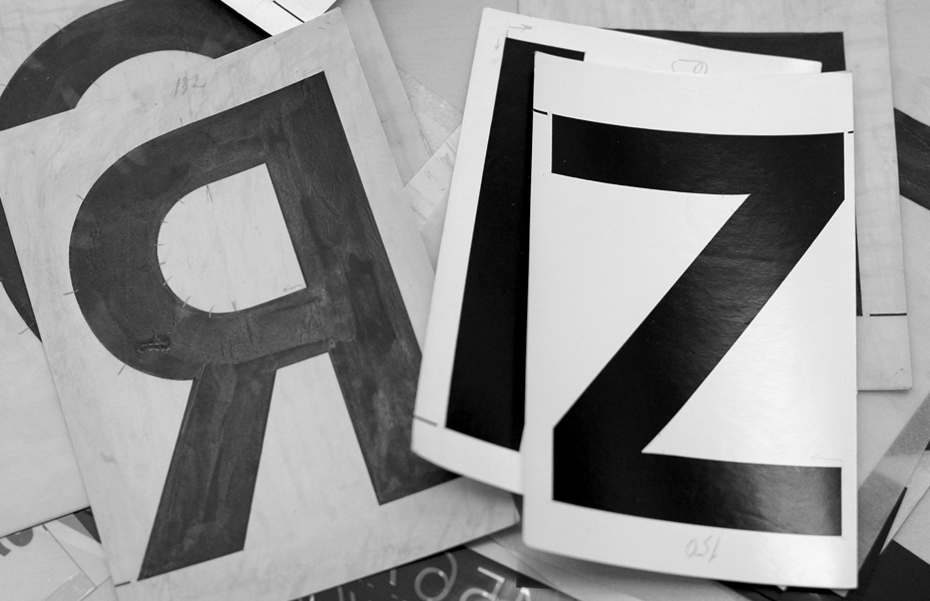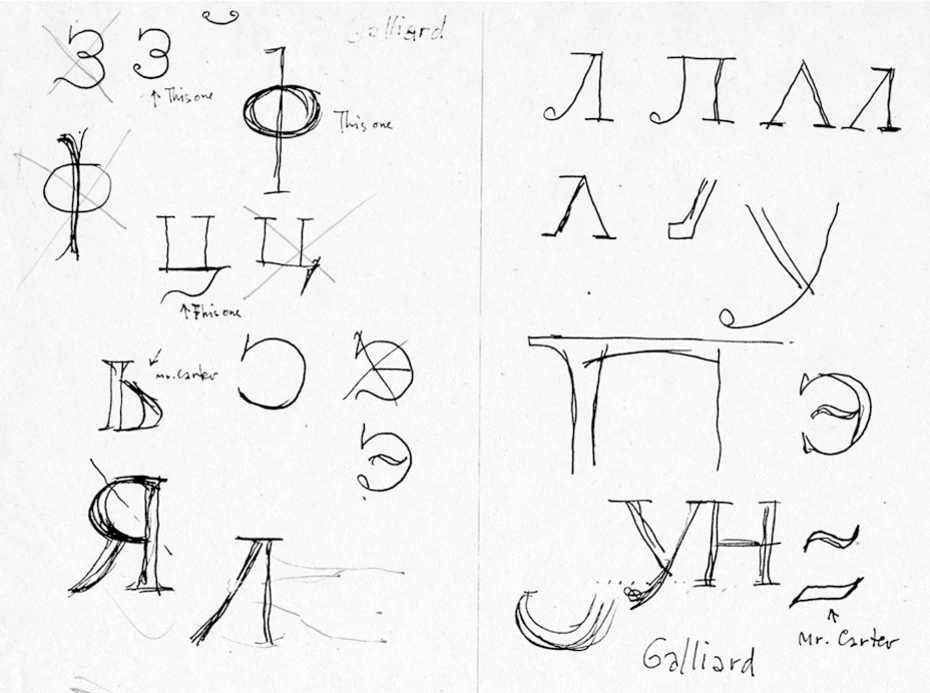
Интервью с Тагиром Сафаевым
ридцатилетний стаж в профессии дизайнера шрифта — для сегодняшней российской действительности явление довольно редкое. Тагир Сафаев прошёл путь от шрифтовых фотонаборных касс и сплайнов программы IKARUS, светящихся на ламповых экранах ЭВМ, до авторской школы шрифта и типографики. Бóльшая часть его шрифтов доступна в каталоге компании «ПараТайп», другие, зачастую эксклюзивные работы — неотъемлемая часть макетов международных издательских домов Axel Springer, Conde Nast и та­ких из­да­ний, как «Афи­ша», «Из­ве­стия», «Российская газета», и мно­гих дру­гих.
Тагир Ибрагимович, когда я увидел в первый раз ваш шрифт Куранта, то не смог найти практически никакой информации о нём, у меня был только плакат с интригующим текстом. Я заинтересовался его природой и пришёл, разумеется, к шрифту Vendôme, но у него наклонное начертание вместо курсива и много других особенностей. Расскажите об этом проекте.
Впервые я увидел Vendôme ещё в школе, тогда он поразил меня силой образа, каким-то притягательным мистицизмом, он настолько насыщен богатой традицией, что накрепко запомнился. Спустя много лет я как-то приобрёл кни­гу о фран­цуз­ском художнике Жор­же де Ла­ту­ре (Georges de La Tour, 1593–1652), и мастерство гениального француза запало в душу. В начале XVII века шрифты во Фран­ции делались всё ещё в парадигме Гарамона, но в это время ста­ло уже по­яв­лять­ся что-то но­вое. И вот, рас­смат­ри­вая Vendôme, я от­крыл для се­бя: это же и есть шрифт той са­мой эпохи. Тогда де Латур вдохновил меня, и я решил попробовать поработать с этим шрифтом, не представляя ещё, что из этого может получиться.
В книге Roger Excoffon et la fonderie Olive о шрифте Vendôme сказано, что эта динамичная и инновационная вариация в стиле Гарамона была работой скульптора, театрального художника Франсуа Гано (François Ganeau). Также указывается, что хотя Роже Экскоффон (Roger Excoffon) не был дизайнером этого шрифта, но он вдохновлял процесс его создания и руководил им, опираясь на своё тонкое стилевое чутьё.
Од­на­ко Vendôme оказался непростым, мно­го­слой­ным шрифтом, и эти слои, на мой взгляд, на­хо­дят­ся в не­ко­то­ром про­ти­во­ре­чии друг с дру­гом. Во-пер­вых, про­пис­ные — это мо­да 50-х го­дов на смелые оригинальные решения, выразительные острые детали, во-вто­рых — ка­жет­ся, что его занятные строч­ные буквы позаимствованы прямо из эпохи Гарамона. И в-третьих — это циф­ры, тоже из 50-х го­дов, но в них совсем иная пластическая интерпретация, нежели в прописных. Герард Ун­гер го­во­рит, что Vendôme — это экстраординарный Га­ра­мон. И ко­гда я ана­ли­зи­ро­вал этот шрифт, смог в этом убе­дить­ся. Вну­трен­няя борь­ба у ме­ня про­дол­жа­лась боль­ше го­да, по­ка я чи­тал де Ла­ту­ра и рас­смат­ри­вал его кар­ти­ны. Я на­чал за­ду­мы­вать­ся, как это можно ис­поль­зо­вать в качестве не­которой тра­ди­ции, что­бы на этом по­ле со­здать но­вое вы­ска­зы­ва­ние.
Шрифт Courante (Куранта), спроектированный Тагиром Сафаевым в 2010 году, — современная реконструкция образа французских барочных антикв начала XX века на основе шрифтов Vendôme (François Ganeau, Fonderie Olive, 1952) и Astrée (Robert Girard, Deberny et Peignot, 1921). Куранта включает в себя три гармонично согласованных системы письменности: латинскую, кириллическую и греческую. Стилистическое решение кириллической части выдержано в духе отечественных шрифтов первой половины XIX века, о чём могут свидетельствовать формы треугольных конструкций букв Л, л, Д, д, а также примечательная форма хвостиков Ц, ц, Щ, щ, подобия которых встречаются в эльзевировских шрифтах словолитни Маврикия Вольфа (Санкт-Петербург, 70–80-е годы XIX века).
Нужно сказать, что я следовал не какой-то конкретной цифровой версии, у меня их просто не было, моим ресурсом были изображения из различных изданий, причём они сильно отличались друг от друга — одно это возбуждало дух экспериментаторства. И в ито­ге я на­чал ра­бо­тать над со­от­вет­стви­ем про­пис­ных зна­ков строч­ным и об­щим един­ством шриф­та. Циф­ры, как полагается в антиквенных шрифтах, сде­лал ми­ну­скуль­ные, ка­пи­тель­ные и ма­юс­куль­ные. У Vendôme вме­сто кур­си­ва на­клон­ное на­чер­та­ние. Я сде­лал настоящий строчной кур­сив, от­ча­сти про­ци­ти­ро­вав кур­сив из фран­цуз­ско­го шриф­та Astrée (Robert Girard, Deberny & Peignot, 1923; позже он будет выпущен в Лондоне в 1926 году под именем Mazarin). И по­том та­кой слож­но­со­чинён­ный про­цесс стал про­дви­гать­ся даль­ше, что­бы сло­жить­ся в не­что еди­ное. В об­щем, счи­таю, что работа по­лу­чи­лась и её нуж­но бы про­дол­жить и за­вер­шить.
С 1995 года в мире было сделано не менее пяти цифровых версий Vendôme. Например, Кристиан Шварц (Christian Schwartz), американский дизайнер, разрабатывал свою версию этого шрифта, но работа осталась незаконченной. Думаю, что это естественный подход к историческим шрифтам — наполнять создаваемый шрифт не­ко­ей су­ще­ству­ю­щей тра­ди­ци­ей и по ме­ре спо­соб­но­стей вно­сить свою ин­то­на­цию, свои пла­сти­че­ские со­об­ра­же­ния, то­гда мо­жет появиться шанс со­здать не­что но­вое и ин­те­рес­ное. Примеров такого подхода множество! В том, что мы транс­фор­ми­ру­ем, раз­ви­ва­ем что-то уже су­ще­ству­ю­щее, нет ни­ка­ко­го «правового про­из­во­ла», на­про­тив, ис­то­ри­че­ский об­ра­зец помогает в начале работы точнее понять задачу, ко многому обязывает в процессе работы, что приводит в конце концов к внятному результату, у ко­то­ро­го бу­дут кон­крет­ные кри­те­рии оцен­ки.
Вы закончили Полиграфический институт и именно там обнаружили интерес к шрифту. Расскажите о вашей учёбе и о том, как вы появились в шрифтовом деле.
Да, со шриф­том я столк­нул­ся, по­сту­пив в По­ли­граф в 1984 го­ду. Мне бы­ло уже за 30, и я ра­бо­тал по ли­нии Со­ю­за ху­дож­ни­ков в гра­фи­ке, цвет­ном эстам­пе. С се­ре­ди­ны 70-х мо­ей основ­ной ра­бо­той в худфонде, ку­да ме­ня на­пра­ви­ли по окон­ча­нии ху­до­же­ствен­но­го учи­ли­ща (1971), ста­ла мо­ну­мен­таль­ная рос­пись в об­ще­ствен­ных зда­ни­ях Астра­ха­ни и об­ла­сти. При­ме­ром мо­гут слу­жить рос­пи­си в ак­то­вом за­ле астра­хан­ской су­до­вер­фи им. С. М. Ки­ро­ва, в фойе го­род­ской шах­мат­ной шко­лы и дру­гие.
В на­ча­ле 80-х я по­пал в дом творчества «Че­люс­кин­ская», где ру­ко­во­ди­те­лем по­то­ка был Алек­сандр Ли­ва­нов. Это уди­ви­тель­ная лич­ность, за­ме­ча­тель­ный пе­да­гог. Я про­сто не от­хо­дил от него, без конца со­ве­то­вал­ся с ним. Кро­ме то­го, сам по­ток со­сто­ял из большого количества про­фес­си­о­на­лов. Ли­ва­нов мне на мно­гое от­крыл гла­за, до­мой я при­е­хал про­сто дру­гим че­ло­ве­ком. В ито­ге я по­нял, что мне не хва­та­ет об­ра­зо­ва­ния, и ре­шил в свои 33 го­да по­сту­пать в ин­сти­тут.
И по­сту­пил, но че­рез не­ко­то­рое вре­мя на­чал со­мне­вать­ся: за­чем я во­об­ще это сде­лал? Ока­за­лось, что Ли­ва­нов там ещё не пре­по­даёт (он стал пре­по­да­вать че­рез три го­да), об­ще­ствен­ные пред­ме­ты — од­на ис­то­рия пар­тии че­го сто­ила — по­гло­ща­ют бóльшую часть времени. Так в неопределённости про­шла не­де­ля, по­ка в суб­бо­ту не по­явил­ся Мак­сим Жу­ков. Буквально после первых занятий у ме­ня пробудился огромный ин­те­рес к шриф­ту и на­чал­ся все­сто­рон­ний про­цесс осо­знан­но­го на­коп­ле­ния зна­ний. То­гда я ото­дви­нул гра­фи­ку и на­чал за­ни­мать­ся ис­клю­чи­тель­но шриф­том.
Именно по-настоящему профессиональное преподавание шрифта с са­мо­го на­ча­ла побудило меня по­грузиться в те­му, рас­смат­ри­вать шрифт в кон­тек­сте ис­то­рии ис­кусств, ли­те­ра­ту­ры, языка, общества и ещё много чего.
Во вре­мя обу­че­ния я по­зна­ко­мил­ся также с Алек­сан­дром Ко­но­плё­вым, ди­зай­не­ром кни­ги. Че­рез Ко­но­плёва и Жу­ко­ва я мно­гое по­стиг в ти­по­гра­фи­ке, в книж­ном ди­зай­не. Ещё был Ми­ша, Михаил Александрович Аникст, ко­лос­саль­ная лич­ность, — я на­про­сил­ся прой­ти прак­ти­ку в его ма­стер­ской, которая была в то время как бы эпицентром, притягивающим молодых людей, вовлечённых в графический дизайн. Чем только не занимался Миша — от кни­г, альбомов до пла­ка­тов, ло­го­ти­пов и прочей айдентики. То­гда все об­хо­ди­лись не­боль­шим ас­сор­ти­мен­том шриф­то­вых касс, а у Ми­ши бы­ло ги­гант­ское ко­ли­че­ство фо­то­на­бор­ных касс — чувство шрифта было на высоте. Не бы­ло ком­пью­те­ров и ска­не­ров — мы вы­чи­ща­ли фо­то­гра­фии, сни­ма­ли, уве­ли­чи­ва­ли, умень­ша­ли, вы­кле­и­ва­ли. Лю­ди всю жизнь этим за­ни­ма­лись, а у Ми­ши представился случай освоить это за год с небольшим. Я по­нял зна­че­ние руч­но­го тру­да для шриф­то­во­го де­ла, все эти умень­ше­ния, мас­шта­би­ро­ва­ния. Это очень по­лез­но — ощу­щать зре­ни­ем, ру­ка­ми. Он первый указал, что дизайнер может и должен вести параллельно с дюжину разнообразных работ, эта динамика позволяет глубже понимать суть профессии.
Темой вашего дипломного проекта стала кириллизация шрифта Frutiger, который позже был выпущен под именем FreeSet. Почему вы выбрали именно его?
Вообще-то, сначала я выбрал дипломным проектом кириллизацию шрифта ITC Slimbach. Но Миша предложил другую идею: «Вот немецкий журнал Form, он набирается шрифтом Frutiger (в 80-х годах в Европе этот шрифт как раз вышел в полной латинской комплектации), хорошо бы иметь его у нас в кириллице». Тогда меня этот журнал поразил качеством дизайна, чистотой исполнения типографических и шрифтовых решений.
В итоге темой моего диплома была кириллизация «Фрутигера», эта работа поглотила меня целиком. Руководителем диплома был Владимир Ефимов — и это тоже было невероятным везением. Ефимов в институте не работал, я его не знал лично. Тогда я попросил Коноплёва познакомить меня с Ефимовым, он позвонил и говорит: «Володя, вот тут студент, хочет, чтобы ты вёл его диплом. Приходи, или он к тебе придёт». Вот я к нему и пришёл и шаг за шагом начал изучать форму кирилловских букв — это была целая наука.
В ито­ге все пять лет я занимался толь­ко шриф­том. На ка­фед­ре по­ня­ли, что жи­во­пис­цем или гра­фи­ком не ста­ну, пя­тёр­ки, прав­да, ста­ви­ли — ра­бо­ты-то у ме­ня хо­ро­шие бы­ли, Cо­юз ху­дож­ни­ков всё-та­ки за пле­ча­ми, и, видимо, пригодился опыт работы в ли­то­гра­фи­и и гра­вю­ре. Ди­плом у ме­ня был на шесть ли­стов фор­ма­та А1: сплошные бук­вы, два пря­мых на­чер­та­ния. Получил пятёрку.
Потом обучение закончилось, это был 1989 год, перестройка шла полным ходом — выпускников вузов уже не так настойчиво отправляли «по направлению» в города и веси. Поэтому я, немного отдышавшись в Астрахани, вернулся в Москву, снял комнату, перебивался маленькими работами по издательствам.
А в 1990 году начались перемены: появилась шрифтовая фирма Azzet, правда, они занимались пиксельными шрифтами. Другая фирма родилась в недрах ОНШ (отдел наборных шрифтов в НИИ «Полиграфмаш»), который присоединился к фирме ParaGraph Int., тогда это называлось советско-американским предприятием, они занимались векторными шрифтами.
Кто в те годы работал в «ПараГрафе»?
События развивались следующим образом. Сначала побывал на встрече в Azzet. Там уже работали Дмитрий Абрикосов, мой сокурсник, Женя Добровинский, Виктор Кучмин — всё знакомые лица. Там в первый раз увидел компьютер. Пока размышлял, что буду делать в Azzet, встретился с Володей Ефимовым, он объявил, что создаётся солидная фирма ParaGraph и в ней будет шрифтовой отдел, и говорит: «Давай-ка ты лучше к нам, в „ПараГраф“». Я прикинул — вроде там тоже интересно, тем более мы с Ефимовым во время работы над дипломом хорошо сработались. И самое главное, они занимались вектором, а не пикселями, с профессиональной точки зрения мне это казалось солиднее. И я пошёл в «ПараГраф».
Располагался он тогда на Трубной, 7, наш отдел размещался в крохотной комнатушке — духотища, жарища, но именно там я впервые сел за компьютер. Мы были шрифтовым отделом «ПараГрафа». Там работали Володя Ефимов, Саша Тарбеев, Любовь Алексеевна Кузнецова, Эльвира Сергеевна Слыш, Исай Соломонович Слуцкер — он уже в возрасте был. Просто звёздный состав. Помните такой шрифт — ITC Franklin Gothic, так вот, когда я увидел, среди прочих букв, рисунок строчной буквы «б», который сделал Исай Соломонович, меня восхитил масштаб его опыта и умений. Это была тонкая и точная работа — он нашёл то самое движение, которое подходит и по пропорциям, и по масштабу. Эта точность и является смыслом нашей работы. Если её нет или нет стремления к этой точности, лучше чем-то другим заниматься.
Шрифт ITC Franklin Gothic Cyrillic. Цифровая версия гарнитуры разработана в фирме International Typeface Corporation в 1980 году (дизайнер Виктор Карузо). Franklin Gothic был спроектирован Моррисом Бентоном и первоначально выпущен фирмой American Type Founders в 1904 году. Версия ITC широко развита по насыщенности и, при слегка зауженных пропорциях и крупном очке строчных знаков, может применяться для набора текста, заголовков и акциденции. Кириллическая версия разработана в фирме «ПараТайп» («ПараГраф») в 1995 году (дизайнеры Исай Слуцкер, Татьяна Лыскова). 12 узких начертаний были добавлены в 2000 году Исаем Слуцкером и Дмитрием Кирсановым.
И с начала 90-х вы c коллегами работали над кириллизацией западных шрифтов, в результате чего в арсенале российских дизайнеров появились приличные шрифты с кириллицей: Баскервиль, Гарамон, Чартер, Франклин Готик, Футура и целый ряд других.
Да, то­гда бы­ла об­щая про­бле­ма: в Рос­сию при­бы­ва­ло всё боль­шее и боль­шее количество ком­пью­те­ров со встро­ен­ны­ми в них си­стем­ны­ми шриф­та­ми, к сожалению, ки­рил­ли­ческих расширений эти шриф­ты не имели, нашим дизайнерам просто не­чем бы­ло ра­бо­тать.
Но опять по­вез­ло: Мак­сим Жу­ков был зна­ком с людь­ми из International Typeface Corporation, и он по­мог «Па­ра­Гра­фу» до­го­во­рить­ся с ITC, что­бы мы мог­ли ки­рил­ли­зо­вать шриф­ты из биб­лио­те­ки. Под­лин­ные ри­сун­ки знаков, ко­то­рые ITC при­сы­лал, по тем вре­ме­нам были невообразимого ка­че­ства.
Затем началась работа, консультации Максима, которые для меня были как бы продолжением образования, начатого ещё в институте. Потрясающее было время.
То­гда был на­сто­я­щий бум! Мак­сим пра­виль­но го­во­рит, что бы­ли «ли­хие 90-е», но для шрифтового цеха это было нечто другое — лю­ди тру­ди­лись и со­зда­ва­ли ба­зу, о которой он рассказал в статье в сборнике Language Culture Type. По мо­е­му мне­нию, в ис­то­рии оте­че­ствен­но­го шриф­то­во­го де­ла со времён ре­фор­м Пет­ра I бы­ло несколько значимых эта­пов, один из которых — ко­нец именно на­ше­го XX ве­ка, ко­гда оте­че­ствен­ный шриф­то­вой ре­пер­ту­ар рас­ши­рил­ся на осно­ве ка­че­ствен­но кириллизованных за­пад­ных шрифтов. Здесь сублимировался огромный предыдущий опыт, традиции латиницы и кириллицы и понимание требования времени.
Вы начинали работать в «Икарусе»?
Мои познания в компьютерных программах минимальны. С годами, конечно, растёт осведомлённость, но акцент у меня всегда в зоне формы буквы, на визуальной точности контура, а не в программном языке описания этого контура, хотя, конечно, в мире требования к программной стороне дела возрастают и дизайнеру рекомендуют «учить матчасть».
С появлением персонального компьютера у программиста ОНШ Андрея Скалдина, естественно, появилась идея переложения системы IKARUS, которая работала на больших производственных компьютерах, на РС. Эта новая программа называлась Fontain, она предназначалась для работы шрифтовых дизайнеров в «ПараГрафе». Во всём мире дизайнеры шрифта работали в программе Fontographer. Разница этих программ была существенной: Fontain имел дело со сплайнами, а Fontographer — с кривыми Безье.
Как раз свой дипломный шрифт FreeSet я делал на опытных версиях программы Fontain, но из-за технических трудностей пришлось работать на оригинальном «Икарусе» в ОНШ. Внешне это огромный тёмно-зелёный, почти чёрный экран монитора, на котором тоненькая ярко-зелёная линия — это контур буквы в сплайнах. При нажатии пары клавиш программа конвертирует контур в кривые Безье, и появляется тоненькая ярко-красная линия. Получил контур, распечатал на плоттере, закрыл тушью — смотришь. Поучительная программа была — приучала чувствовать едва заметные изменения контура в сплайнах, стараться, чтобы они в Безье правильно отображались при конвертации.
Каким был следующий шрифт после Фрисета?
По­сле Фри­се­та я, ко­неч­но, хо­тел за­мах­нуть­ся на ITC Га­ра­мон, но это­го не слу­чи­лось: Га­ра­мон до­стал­ся Са­ше Тар­бе­е­ву. Всё к луч­ше­му. По­ру­чи­ли ITC New Baskerville. Мне по­вез­ло вдвой­не. Во-пер­вых, ITC New Baskerville — вы­со­кая клас­си­ка в чи­стом ви­де. Гар­ни­ту­ра бы­ла ли­цен­зи­ро­ва­на фир­мой ITC в 1982 году у фир­мы Mergenthaler Linotype. Это раз­ра­бот­ка Джо­на Ка­ран­та 1978 го­да. Вто­рое: по­лу­чив кар­тин­ки со шриф­та­ми, ста­ло из­вест­но, что Мак­сим Жуков бу­дет кон­суль­ти­ро­вать на­шу ра­бо­ту. Его ком­мен­та­рии к шриф­там мы по­лу­ча­ли по­чтой, чи­та­ли их и ис­прав­ля­ли сде­лан­ное — он пи­сал про каж­дую бук­ву, что с ней нуж­но сде­лать. Во­об­ще, очень важ­но бы­ло уча­стие Мак­си­ма в про­ек­тах шриф­тов ITC, это труд­но пе­ре­оце­нить.
В 1982 году аме­риканс­кая фирма ITC ли­цен­зи­рова­ла у фирмы Mergenthaler Linotype новый ва­ри­ант шриф­та Baskerville и назвала его ITC New Baskerville в 8 на­чер­та­ни­ях. Он был соз­дан груп­пой ди­зай­не­ров под ру­ководс­твом Джона Ка­ран­та. Ки­рил­ли­чес­кую вер­сию этого шриф­та для компании «ПараТайп» раз­ра­ботал в 1993 году Тагир Са­фа­ев.
На­при­мер, я сра­зу улав­ли­вал, о чём Мак­сим пи­шет, от­ку­да у не­го воз­ни­ка­ет та или иная идея. Мак­сим ведь за­кон­чил учё­бу в середине 60-х и с тех пор систематически работал над шрифтами, шёл к однажды выбранной цели. В со­вет­ское вре­мя шриф­то­вой ди­зай­нер мог толь­ко на об­лож­ку «Ко­лоб­ка» или «Гро­зы» Остров­ско­го на­ри­со­вать что-то — и всё! А Мак­сим, с его глубокими познаниями, де­ся­ти­ле­ти­я­ми вы­на­ши­вал идеи для ки­ри­ллов­ских шриф­тов. И аль­янс с ITC — это ре­а­ли­за­ция замыслов, зревших в те са­мые де­ся­ти­ле­тия.
Вы проектировали кириллицу для нескольких проектов Мэтью Картера. Такого рода сотрудничество, конечно, дорогого стоит. Как выстраивалась работа с мистером Картером?
Это вер­но. На шриф­тах Мэтью Кар­те­ра, мож­но ска­зать, я вы­рос! Их было несколько. В 1995 го­ду в «Па­ра­Гра­фе» решили ки­рил­ли­зовать два шриф­та, и это нуж­но бы­ло с че­стью вы­пол­нить: ITC Charter и ITC Galliard. По­сколь­ку оба шриф­та сде­лал Кар­тер, не бы­ло ре­чи, что луч­ше или ху­же. Мы с Во­ло­дей вы­ки­ну­ли на паль­цах, кому что достанется, вышло: ему — Чар­тер, мне — Га­льярд. Если честно, хотелось именно ITC Galliard, потому что это легенда, его характеризуют как мощный, буйный, яркий, даже чувственный. Поразительная история у этого шрифта!
Мэтью Картер сделал шрифт Galliard в 1978 году для фотонаборных машин компании Mergenthaler Linotype Company. В журнале U&lc; 1981 года под рубрикой What’s new from ITC перед крупно напечатанными алфавитами Galliard’a сказано: «Эта прекрасная современная реконструкция шрифтов [французского художника шрифта, гравёра и печатника] Робера Гранжона (Robert Granjon, 1513–1590) XVI столетия была создана дизайнером Мэтью Картером. Картер использовал компьютер, чтобы спроектировать систему начертаний, соответствующую требованиям XX века. <...> Дизайнер Картер провёл очень деликатную работу, воплотив дух шрифтов Гранжона в современной разработке, отличающейся подтянутой, энергичной формой знаков и высоким ростом строчных. Прямые и курсивные начертания при всей своей выразительности прекрасно читаются в наборе объёмных текстов».
Картер писал письма, в которых он очень подробно комментировал, что и как нужно сделать, всё было очень цивильно оформлено: на бланке, без суеты. Он присылал выведенные с пантографа изображения кирилловских букв, которых не хватало, я их сканировал и работал уже с ними.
Как вы­стра­и­ва­лась ра­бо­та Кар­те­ром? В основном я работал с Максимом, а он уже общался с Картером, когда что-то было непонятно. Максим, естественно, с ним советовался. У меня сохранилась картинка, на которой Максим рисовал формы, показывал мистеру Картеру, а тот уже дорисовывал. Например, написано: я такая может быть, а он — No. А вот мистер Картер нарисовал, как Ц курсивную нужно делать или как г курсивную — там сложнейшая форма.
К со­жа­ле­нию, ко­гда я за­кон­чил два на­чер­та­ния, в 1995–1996 го­дах, у ITC воз­ник­ли про­бле­мы, а в 2000 го­ду они сменили владельца. Было объявлено о «смутном времени». Но­вое ко­ман­до­ва­ние отложило ITC Galliard в план следующего года. Проект, над ко­то­рым я ра­бо­тал около го­да, остал­ся не­за­вер­шён­ным. Я бы сей­час с боль­шим удо­воль­стви­ем про­дол­жил ра­бо­ту над Га­льяр­дом. По­тря­са­ю­щей кра­со­ты шрифт.
Вопрос о шрифте Cheltenham. Я видел две версии шрифта для разных макетов — для журнала Forbes и для русскоязычного издания The New York Times и помню, что меня удивило, насколько разным был образ и даже возраст кириллицы в этих шрифтах.
Это для ме­ня це­лая эпо­ха. Ко­гда я ра­бо­тал для «Форб­са», то сде­лал пер­вое на­чер­та­ние ITC Cheltenham. Во­об­ще, Cheltenham — это пре­крас­ная мо­дель. Сам шрифт спро­ек­ти­ро­вал в 1896 го­ду Бер­трам Гуд­хью (Bertram Grosvenor Goodhue) и Ин­галс Ким­бол (Ingalls Kimball) для Cheltenham Press, а позд­нее его пе­ре­ра­бо­тал Мор­рис Бен­тон (Morris Fuller Benton) для American Type Founders Company. И эти вер­сии силь­но от­ли­ча­ют­ся по сво­е­му ду­ху от то­го, что сде­лал по­том ITC. На са­мом де­ле у шриф­та бо­лее ар­ха­ич­ная, вик­то­ри­ан­ская осно­ва, у не­го да­же оси чуть на­клон­ные. А в ITC обоб­щи­ли и сде­ла­ли его бли­же к пе­ре­ход­но­му сти­лю, точнее к New Transitional.
Американский архитектор Бертрам Гудхью (Bertram Grosvenor Goodhue, 1869–1924) был известен как один из участников архитектурного движения «готического Возрождения» на рубеже XIX–XX веков. В 1896 году Гудхью применил свои таланты в шрифтовом дизайне, когда Дэниел Апдайк (Daniel Berkeley Updike) из Merrymount Press в Бостоне заказал ему изготовление заглавий для церковной книги. Обратив внимание на впечатляющий результат, Ингалс Кимбол (Ingalls Kimball) заказал Гудхью разработку нового шрифта для эксклюзивного использования в своём нью-йоркском издательстве Cheltenham Press. Кимбол приготовил первые эскизы прямого начертания, а Гудхью сделал на их основе тот самый шрифт, который впоследствии стал завсегдатаем американских издательств и звался печатниками не иначе как Chelt. Это была идея именно Гудхью — разработать книжный шрифт, в котором будет на первое место поставлена удобочитаемость. Гудхью поддерживал идею о том, что верхняя часть строки шрифта намного важнее для распознавания знаков и чтения текста, поэтому увеличил верхние выносные элементы и сделал короче нижние. Это нововведение также отразилось и на ёмкости набора, позволив существенно сократить межстрочное расстояние. В 1902 году права на использование дизайна шрифта приобрела фирма American Type Founders (ATF), художественным руководителем которой был легендарный Моррис Бентон (Morris Fuller Benton), он же разработал широкое количество стилей и начертаний этого шрифта и выпустил его в публичную продажу как первую в своём роде «шрифтовую семью».
Ко­гда я ра­бо­тал в шта­те «Из­ве­стий», руководство газеты ре­ши­ло по­дру­жить­ся с The New York Times и вы­пус­кать дай­джест — вос­крес­ное при­ло­же­ние на ан­глий­ском язы­ке. Но у нас не так мно­го лю­дей сво­бод­но вла­де­ет ан­глий­ским, как пред­по­ла­га­ли в NYT, по­это­му через некоторое время воз­ник­ла не­об­хо­ди­мость выпускать дай­джест русскоязычным. И мне пред­ло­жи­ли сде­лать ки­рил­ли­ческие версии используемых там шриф­тов. Это были NYT Cheltenham, Imperial, ATF Franklin Gothic плюс ряд дополнительных. Поначалу этот вкладыш NYT показался довольно про­стым по типографике, но, вглядываясь, осознаёшь качество типографики и использованных там шрифтов. Шрифт NYT Cheltenham по­явил­ся в га­зе­те в 2003 го­ду (хо­тя уже с 1907 го­да его пра­ро­ди­тель ре­гу­ляр­но ис­поль­зо­вал­ся на пер­вой по­ло­се из­да­ния наряду с другими шрифтами). И для об­нов­ле­ния га­зе­ты бы­л сде­ла­н большой диапазон начертаний: ши­ро­кие, уз­кие, нор­маль­ные, всё расписано по кеглям. Кро­ме прочего, зная о том, что эти шриф­ты сде­лал Кар­тер, я, ко­неч­но, сра­зу со­гла­сил­ся. Было удивительное время: я сдружился с этим шрифтом и со всеми его вариантами. Imperial, ATF Franklin Gothic сразу пополнились кириллицей. А шрифт NYT Cheltenham я продолжал разрабатывать ещё долгое время и, даже сделав необходимое количество начертаний, хотел сделать дополнительные начертания. Но экономическая ситуация изменилась, и работу пришлось остановить. Написал Картеру письмо о том, что произошло с газетой и с его шрифтом.
Сей­час мне поручили сделать новый фирменный шрифт на основе Чел­тен­хема, опять возвращаюсь, анализирую, сравниваю и роясь в разных архивах. Я нашёл пять основных версий: ATF Cheltenham, Sorbonne, Академическая, ITC Cheltenham, NYT Cheltenham, все они разные, и в каждом решались и пластические, и практические задачи. Для заказчика нового шрифта я уже сформулировал эти задачи, осталось продолжить работу с прекрасной идеей.
На одной из открытых лекций в прошлом году вы говорили, что работаете над своей версией шрифта Helvetica. Было бы интересно взглянуть.
Да, я сде­лал «свою» ки­рил­ли­цу для Гель­ве­ти­ки, од­но на­чер­та­ние. Сде­лал как идею, как я её чув­ствую. На мой взгляд, ки­рил­ли­ца Гель­ве­ти­ки долж­на быть со­всем дру­го­го сти­ля, сти­ля 50-х го­дов, и она долж­на от­тал­ки­вать­ся от Ак­ци­денц-гро­те­ска. И я сде­лал шрифт с учётом это­го. Есть та­кой про­ект — Helvetica World, его де­лал Джон Хад­сон, видимо, с кон­суль­та­ци­ей Мак­си­ма. Они там, ко­неч­но, хватанули кру­то. Я чуть про­ще сде­лал, и, мне ка­жет­ся, си­дит оно луч­ше: Гель­ве­ти­ка ста­но­вит­ся рус­ской, упро­ща­ют­ся на­ши ки­рил­ли­че­ские осо­бен­но­сти. На эту тему разговаривал со многими дизайнерами, типографами, каждый на свой лад говорил, как было бы хорошо иметь у нас этот шрифт.
Евгений Ганнушкин в одном интервью сказал о проявлении автора в шрифте: «Я всегда вижу, когда шрифт делал мужчина энергичный, а когда вялый, который не может рассердиться, воскликнуть, в котором нет страсти, напора. И дело не только в пластических излишествах. Дело в том, что шрифт впитывает всего человека. Сколько бы художник ни думал, он никуда не скроется. Он остаётся в своём шрифте весь, целиком, вся его натура и всё его отношение к жизни». Мне интересно ваше мнение по поводу этого соображения.
Если речь идёт о ка­че­ствах, ко­то­рые даются человеку свыше, и он сообразно своему внутреннему состоянию порождает вокруг себя характерную только для него объективную реальность, то именно эта «характерная объективная реальность» ценна — она наполняет жизнь вокруг. Мы живём в ми­фи­че­ски­х фор­ма­х наших предшественников, ко­то­рые за­пол­ня­ем сво­ей «характерной объективной реальностью». Если мы этого не делаем, то этим занимаются дру­гие по­ко­ле­ни­я, а мы остаём­ся за бор­том. На при­ме­ре ки­но: по­ни­ма­е­те, про­сто так ни­кто не сде­ла­ет «Груз 200». У Ба­ла­ба­но­ва го­ре­ло всё вну­три — вот он и снял этот фильм. Ко­гда в шриф­те ав­то­ру удаётся во­пло­тить эту свою «ха­рак­тер­ную ре­аль­ность», шрифт бу­дет дол­го жить и бу­дет иметь со­дер­жа­ние, даже если сам автор не успеет завершить — завершат другие. Прекрасный пример — история шрифта Vendôme.
У нас не стоит задача любой ценой сделать шрифт. Новых шрифтов много. Нам нужны не новые шрифты, а хорошие, наполненные содержанием личности.
Что до вопроса о личности, тут я как суфий: высшее проявление — это красота, которая создаётся талантом. Туда входят и личность, и её самовыражение. Когда я встречаю в авторе (или шрифте — через шрифт и автора видишь) талант, то пытаюсь понять, какие мотивы у него были. Мы разгадываем загадку природы. Или другой при­мер — Эрик Гилл. По­тря­са­ю­ще­го мас­шта­ба лич­ность, он был и ка­ме­нотё­сом, и гравёром, и шрифтовым дизайнером. Добавим, что сексуальная жизнь у него была экс­тра­ор­ди­нарна, но это ведь тоже своя «характерная объективная реальность». Вот и в Gill Sans нет осо­бой упо­ря­до­чен­но­сти и ло­гич­но­сти. Его со­здал ге­ний, и это по­ра­жа­ет, это­му невоз­мож­но на­учить­ся.
Как объяснить такое явление? Никак. Просто нужно понимать, что одной логики недостаточно, чтобы любить эту профессию, особенно в случае с кириллицей. Ты быстро поймёшь какие-то принципы, и они будут примитивны. А что дальше делать — непонятно. Гений же вдохновляет на другом уровне. Если у тебя нет возвышенных идей, нужна сверхсильная аргументация, чтобы заниматься кириллицей, потому что в ней особой поэзии нет.
Приходится часто слышать о том, что кириллица молода, а латиница «созревала веками», что развитие кириллицы ещё впереди. Что именно, на ваш взгляд, означает в этом контексте «развитие»?
Ки­рил­ли­ца мо­ло­да, а ла­ти­ни­ца «со­зре­ва­ла ве­ка­ми» — это оче­ви­дно, ка­за­лось бы, о чём здесь дис­ку­ти­ро­вать? В та­ком кон­тек­сте срав­ни­вать ки­рил­ли­цу с ла­ти­ни­цей — на­прас­ная тра­та вре­ме­ни, лич­но мой ин­те­рес вы­зы­ва­ет са­мо со­дер­жа­ние ки­рил­ли­цы, а не со­сто­я­тель­ность её на фо­не ла­ти­ни­цы или лю­бой дру­гой си­сте­мы пись­мен­но­сти.
Во­об­ще, это со­мни­тель­ный настрой — «мы бы ра­ды, да нуж­но вре­мя», по­это­му ре­фор­ма Пет­ра и остаёт­ся са­мой яр­кой стра­ни­цей в на­шей ис­то­рии. Прав­да, в на­ча­ле 90-х в фир­ме «ПараГраф», как я и го­во­рил, уда­лось со­здать не­что по-на­сто­я­ще­му зна­чи­мое. Ра­бо­ты по ки­рил­ли­за­ции шриф­тов фир­мы ITC и не­ко­то­рые дру­гие про­ек­ты обоб­щи­ли пре­ды­ду­щий опыт рос­сий­ско­го шриф­то­во­го ди­зай­на и спо­соб­ство­ва­ли за­ро­жде­нию но­во­го ви­де­ния для даль­ней­шей ра­бо­ты. Вот как од­но де­ся­ти­ле­тие в три­ста лет может изменить ситуацию!
До­на­тас Ба­ни­о­нис лю­бил по­вто­рять: «Не ищи­те в ис­кус­стве но­вое, ищи­те веч­ное». Толь­ко из этих «веч­ных» на­хо­док, от­кры­тий скла­ды­ва­ет­ся тра­ди­ция в лю­бом де­ле, в том чис­ле и шриф­то­вом.
К сло­ву, о раз­ви­тии. Вы долгое время вели творческую мастерскую в ВАШГД, а два года назад открыли собственную школу шрифта и типографики. Рас­ска­жи­те, по­жа­луй­ста, о ва­шей пре­по­да­ва­тель­ской де­я­тель­но­сти.
Преподавание стало для меня чем-то естественным после первого урока в Национальном институте дизайна, а после двух выпусков в ВАШГД я организовал свои курсы шрифта и типографики совместно с Институтом бизнеса и дизайна.
Сознание, что хоть как-то участвуешь в процессе образования, формирования личности (будь то свои дети или студенты), парадоксальным образом придаёт силы моей мистической работе — шрифтовой. Создавать шрифт — это как поднимать штангу или прыгать с шестом, где борьба идёт не с противником, а c мистическим снарядом, поэтому нужна приземлённость, общение с живыми людьми.
Подготовка у желающих поступить, как правило, довольно слабая, поэтому много времени уходит на формирование хотя бы коллективной энергии. Недостаток подготовки быстро всплывает в те счастливые моменты, когда работа всего курса проходит «в едином порыве», когда, казалось бы, нужно радоваться за результаты работ своих студентов. Нужно терпение, методичное осваивание недопонятого, а жёсткая программа в таких случаях едва ли спасёт. И здесь главное — не навредить.
«Передача знания» — это оксюморон, передавать знания непосредственно как нечто разом данное и очевидное невозможно. «Сейчас я прочту энное количество книг и стану взрослым». Так не бывает. Нужны многообразные усилия, чтобы сформировать свои знания.
«When do letters become too out of the ordinary? Roger Excoffon and François Ganeau’s Vendôme of 1952 is somewhat out of the ordinary because the letters all lean slightly to the right, in the direction in which we read, and because the details are uncommonly sharp. In essence, however, Vendôme is a conventional design, the basic forms of which are surprisingly close to the type of Garamond — making it a very French design». — Gerard Unger, While You’re Reading, 2009, Niggli AG
Ху­до­же­ствен­но-про­из­вод­ствен­ные ма­стер­ские Ху­до­же­ствен­но­го фон­да РСФСР.
«Му­зы­ка фран­цуз­ско­го ком­по­зи­то­ра Ро­бе­ра де Ви­зе, кар­ти­ны ху­дож­ни­ка Жор­жа де Ла­ту­ра и шриф­ты на гра­вю­рах той эпо­хи — се­ре­ди­ны XVII ве­ка — спро­во­ци­ро­ва­ли по­иск шриф­та, ко­то­рый бы со­от­вет­ство­вал то­му вре­ме­ни, ди­на­мич­но­го и остро­го. Так по­явил­ся Courante, тек­сто­вый шрифт, ко­то­рый на рус­ском зву­чит как Ку­ран­та».
Со­вет­ская гра­фи­ка 75/76. Сбор­ник ста­тей. М.: Со­вет­ский ху­дож­ник, 1977.
По­дроб­нее о кри­вых Безье и сплай­нах, а так­же об осо­бен­но­стях устрой­ства пер­вых ком­пью­тер­ных шриф­то­вых про­грамм мож­но узнать в кни­ге Пе­те­ра Ка­ро­ва «Шриф­то­вые тех­но­ло­гии: опи­са­ние и ин­стру­мен­та­рий» (М., «Мир», 2001. Пе­ре­вод с ан­глий­ско­го О. Кар­пин­ско­го, И. Ку­ли­ко­вой под ре­дак­ци­ей, с пре­ди­сло­ви­ем и до­пол­не­ни­ем В. Ефи­мо­ва).